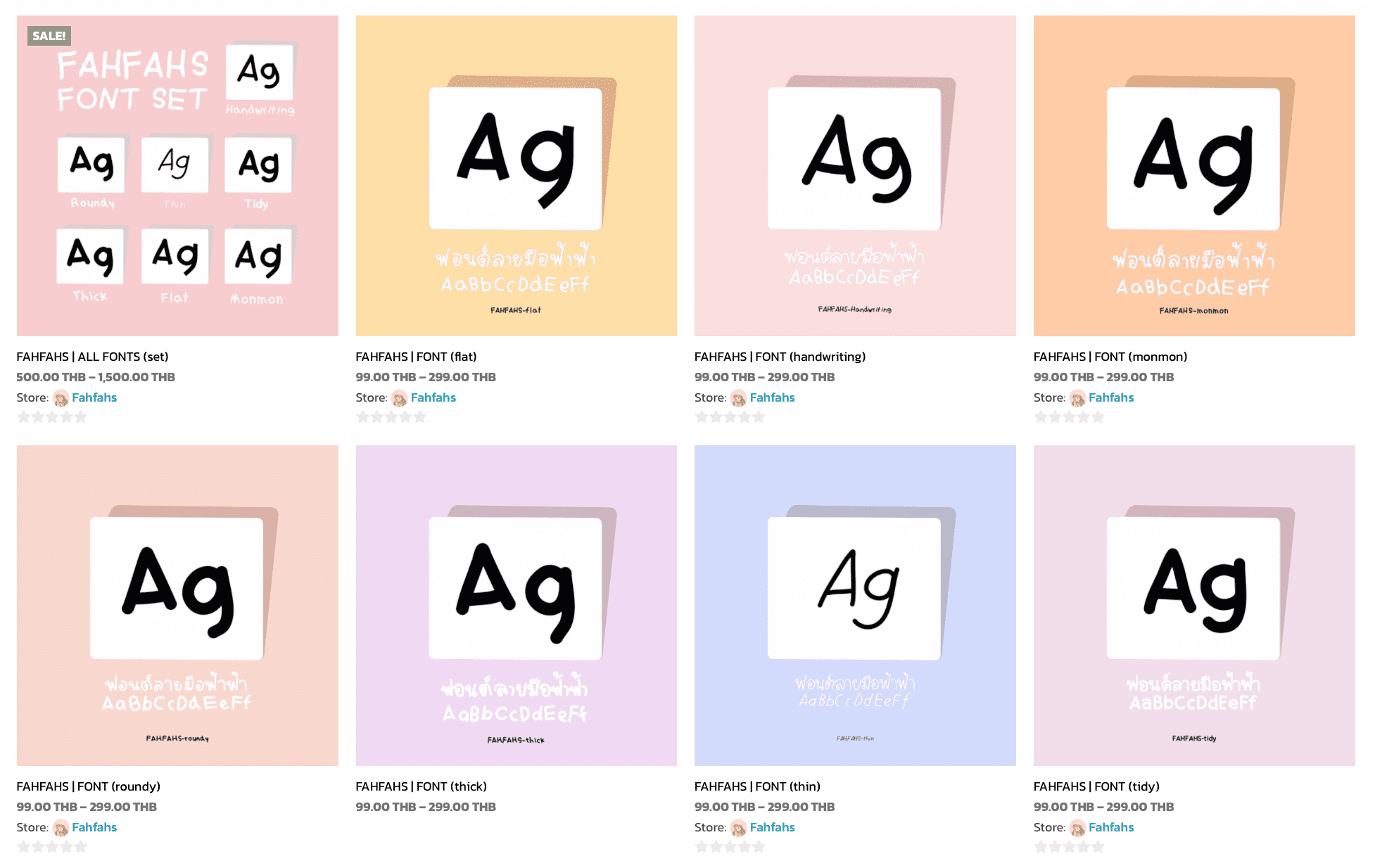
แนะนำฟอนต์ลายมือน่ารักๆ
ใครชอบจดโน๊ตแบบดิจิตอล ทำแพลนเนอร์ออนไลน์ ทำคอนเทนต์ กราฟฟิคขายสินค้าต่างๆ
แล้วกำลังมองหาฟอนต์ลายมือน่ารักๆ ภาษาไทยและภาษาอังกฤษ วันนี้เราขอแนะนำฟอนต์ลายมือฟ้าฟ้า ค่าาาา ><
นั่นก็คือฟอนต์ลายมือของเราเอง (โดยฟอนต์จะมีวรรณยุกต์ที่อยู่ตำแหน่งสูงกว่าฟอนต์ปกติเล็กน้อย)
ตอนนี้ทำออกมามีทั้งหมด 7 แบบ ไปดูกันเลย
7 ฟอนต์ จะสไตล์คล้ายๆกันแต่มีความน่ารักในคนละแบบ ยังคงความปุ๊กปิ๊กกลมๆ เหมาะกับคนที่ต้องการเพิ่มความน่ารักให้กับบทความหรืองานเขียน FAHFAHS Handwriting , Tidy , Flat , Thin , Roundy , Thick และ Monmon
FAHFAHS handwriting font
เป็นฟอนต์แรกที่ทำแจกให้ทุกคนใช้ฟรีๆ อยู่พักนึงเลยค่ะ ได้กระแสตอบรับดีเกินคาด แฮ้ปปี้มาก เลยทำให้มีกำลังใจในการทำฟอนต์มากขึ้นอีก ตอนนี้เปลี่ยนมาให้โหลดในเว็บแล้วมีการปรับเปลี่ยนราคาให้เท่าฟอนต์อื่นๆน้า ฟอนต์นี้จะมีเส้นที่ค่อนข้างบาง เขียนแบบเอียงไปเอียงมาในแบบ random
FAHFAHS tidy font
ฟอนต์ไทดี้ มีความเป็นระเบียบ ให้ลุคสาวเรียบร้อยอ่อนหวาน ตั้งใจคัดลายมือ อ่านง่าย
FAHFAHS flat font
ฟอนต์แฟลต เป็นฟอนต์ type เดียวกับมนมนเลยค่ะ หัวกลม มีการเว้นระยะห่างระหว่างตัวอักษรเล็กน้อยเพื่อเพิ่มความน่ารัก แต่ว่าจะเปลี่ยนหัวแปรงที่ใช้เขียนเป็นปลายตัด ให้ความรู้สึกเหมือนใช้ปากกามาร์กเกอร์เขียน
FAHFAHS thin font
ฟอนต์ตัวผอมบางและเอียง ดูแรงน้อยกว่าใครเพื่อน แต่สำหรับใครที่ชอบตัวบางๆ สบายตาก็แนะนำฟอนต์นี้เลย
FAHFAHS roundy font
ฟอนต์ราวดี้ตัวอ้วน มน กลม ชื่อแอบเติมดี้ให้ดูน่ารักขึ้น อันนี้ปุ๊กปิ๊กมากๆ เส้นหนา ตูดตัวอักษรจะมีความโค้งมน
FAHFAHS thick font
ฟอนต์ตัวหนาที่สุดในบรรดาฟอนต์ลายมือของฟ้าเลยก็ว่าได้ อันนี้คิดว่าถ้าทำเป็น head หัวข้อ หรือกราฟฟิคที่ต้องการเน้นคำก็จะน่ารักเกินต้านไปเลยค่า
FAHFAHS monmon font
ฟอนต์มนมนเป็นฟอนต์หัวกลม มีความปุ๊กปิ๊กคล้ายๆฟอนต์แรก แต่ว่าจะดูเป็นระเบียบกว่า มีช่องไฟมากขึ้น ใช้ทำกราฟฟิคแล้วคือน่ารักที่สุด ฟ้าชอบฟอนต์นี้เป็นพิเศษเลยค่า